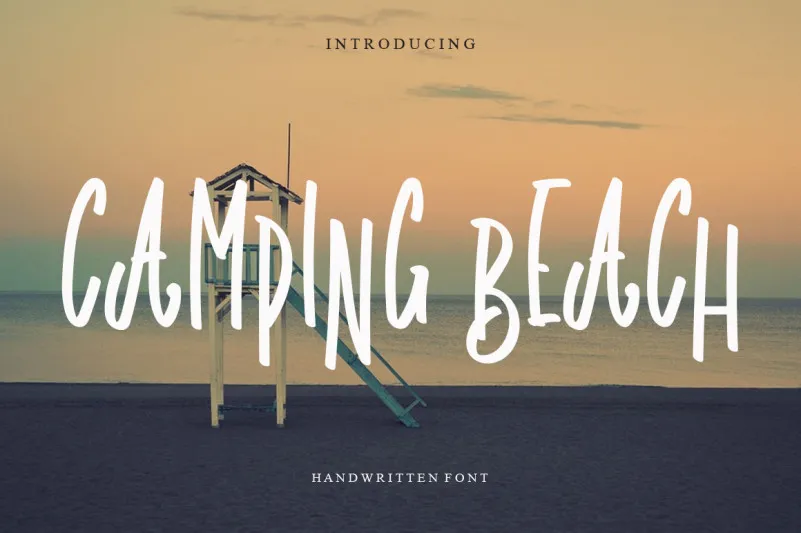
Aqui está uma descrição envolvente para a página de download da font ‘Camping Beach Font’, adaptada ao estilo solicitado: Estamos ansiosos para apresentar a nova Camping Beach Font, um projeto criativo que traz à tona um estilo charmoso e acolhedor. Confeccionado pela talentosa equipe do levincreative, este é um font script exclusivo com uma escrita manuscrita envolta em atmosferas despreocupadas e descontraídas. Ideal tanto para designers de perfil jovem e criativos quanto para aqueles que valorizam uma paixão pelo design original e autêntico. Com a Camping Beach Font, você pode transformar qualquer projeto em uma verdadeira obra-prima artística – seja ela um post amigável no Instagram ou um delicado elemento de escrita por chamamento para seu próximo DIY. Este é mais do que apenas um recurso visual: ele é um artefato de inspiração e criatividade, pronto para moldar a forma como você expressa sua visão pessoal. Seja você um amante da web ou um artista freelance, a Camping Beach Font tem o poder de adicionar um toque único e divertido à sua próxima peça de trabalho. Sua elegância manuscrita traz vida ao seu design e cria uma conexão instantânea entre o público que percebe essa paixão pela natureza e a beleza do convívio social. Essa font é perfeita para aqueles amantes da praia, dos fãs de camping ou mesmo para qualquer pessoa procurando por um visual único para seu próximo projeto. Adote esta font em suas próximas criações e permita que ela seja uma expressão do seu próprio estilo, desenhado na areia da vida.